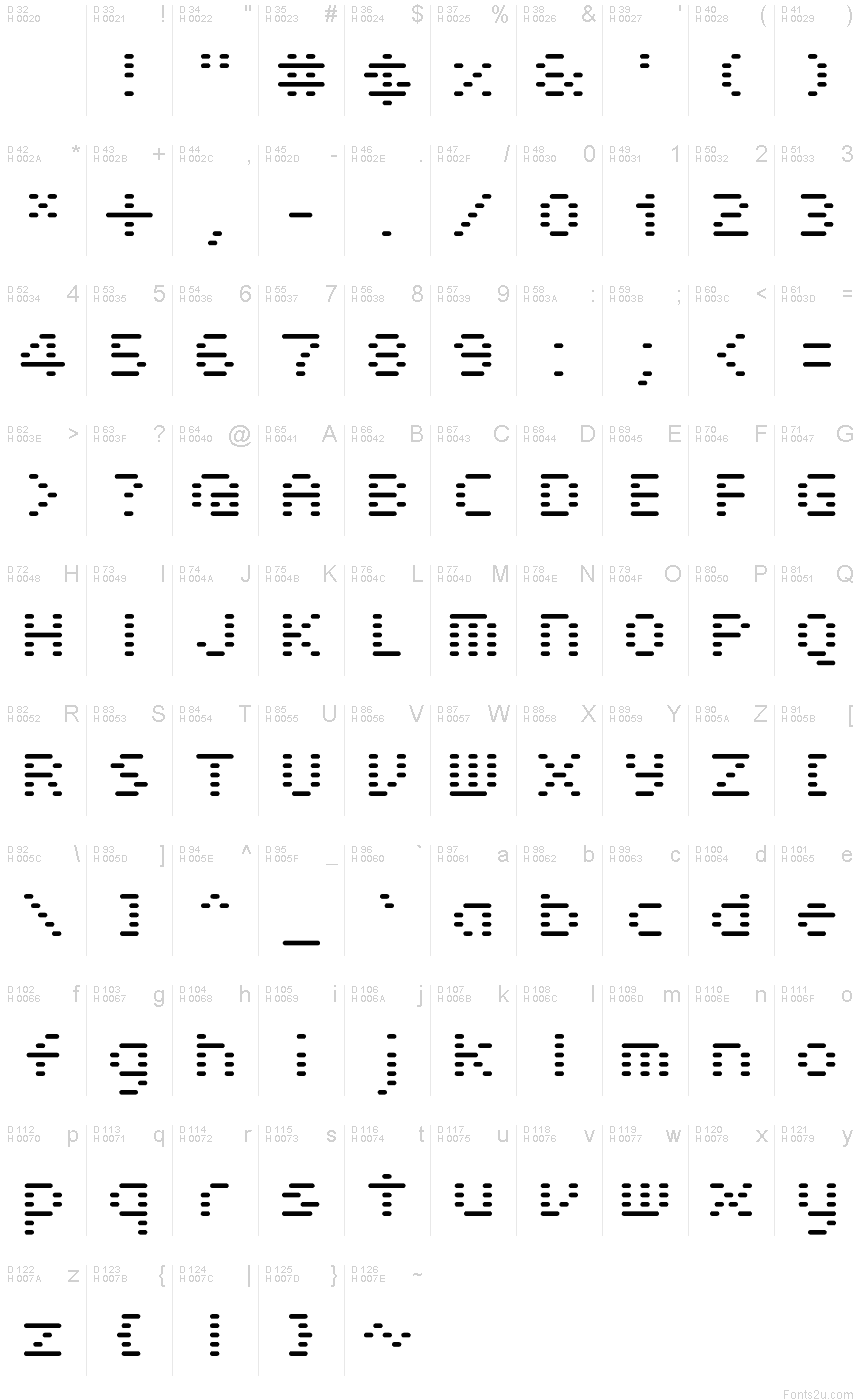
خط Cardew Three Rounded من Someshinzz هو خط عرض رقمي مجاني مصمم من أشرطة أفقية مستديرة. تذكرنا حروفه المقسمة بعدادات LED ولوحات النتائج الإلكترونية المبكرة. تجعل الفجوات الواسعة كل شكل يبدو وكأنه مُجمَّع وليس مرسوماً.
يمكن للمصممين الذين يعملون في مواضيع الألعاب، أو الرياضة، أو التكنولوجيا استخدامه في رسومات الألعاب وملصقات الفعاليات. كما أنه مناسب للبضائع المستوحاة من لوحات النتائج. يمكن للقطع على شكل حبة الدواء أن تحاكي أزرار واجهة المستخدم، أو أضواء الحالة، أو الرسوم التوضيحية بأسلوب البكسل، مما يحول الحروف إلى جزء من المشهد البصري.